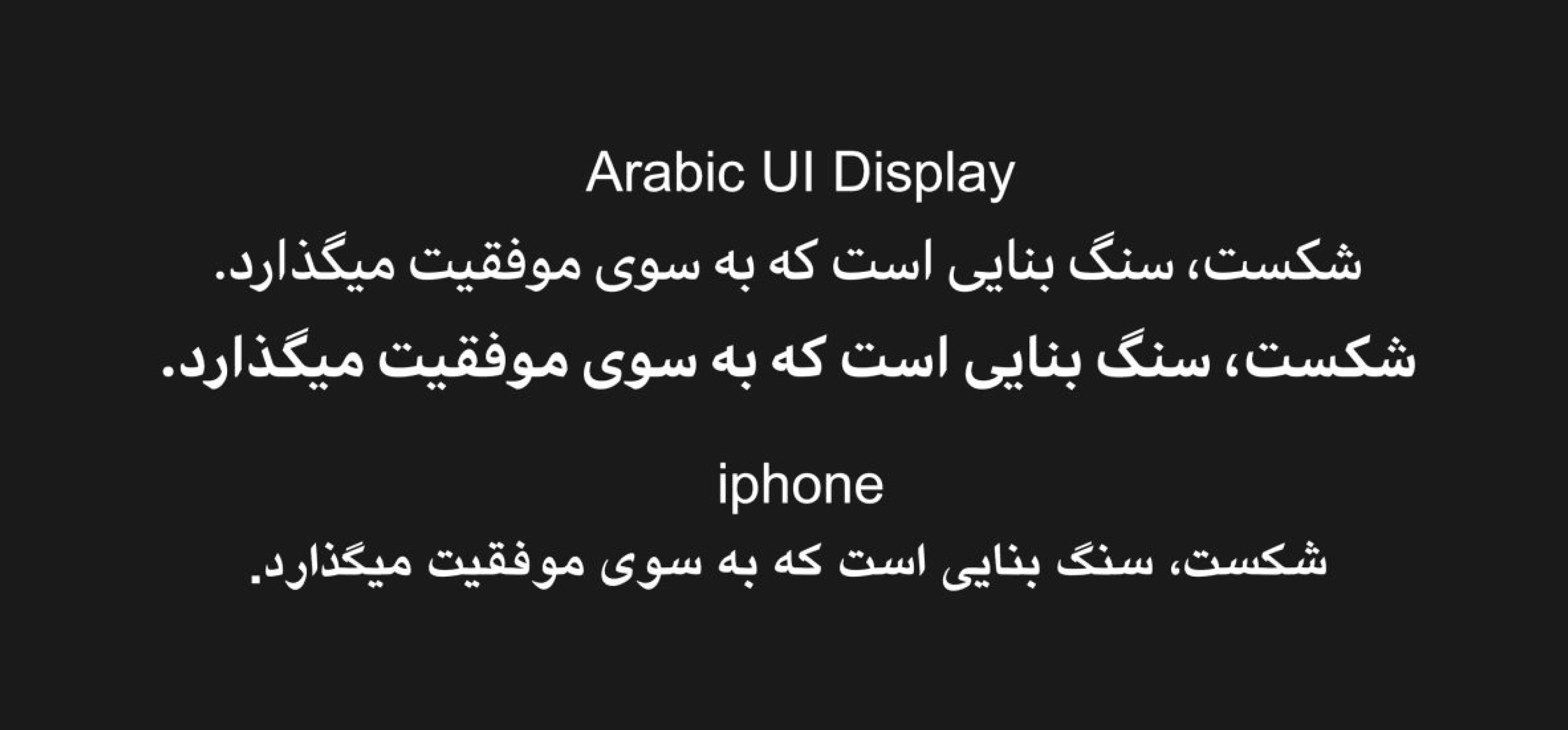
للحصول على مظهر موحد واحترافي في تصاميمك، يمكنك الاستفادة من تحميل خط الآيفون الفارسي مجانًا، وهو نفس الخط المستخدم في أجهزة Apple.
يتميز هذا الخط بتصميم جميل ووضوح عالٍ، مما يمنح النصوص طابعًا عصريًا وجذابًا، ويساعد على جعل تصاميمك تبدو أكثر احترافية وجودة.